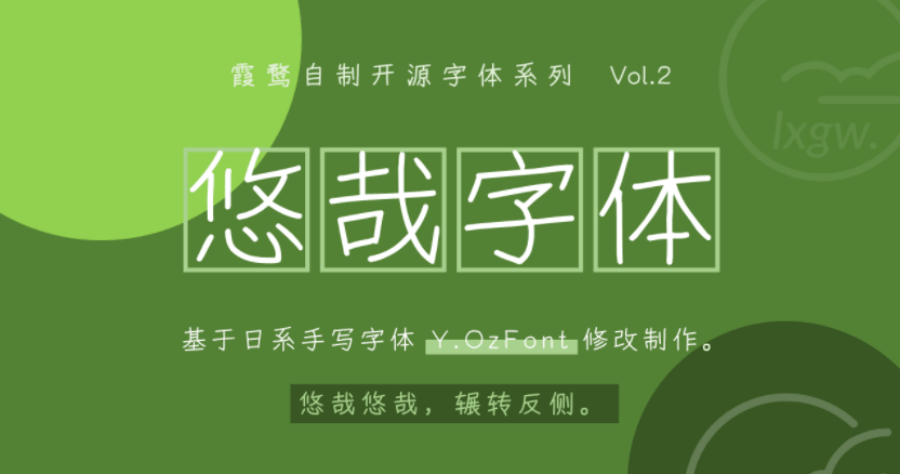
想安裝風格不同的「手寫字體」嗎?最近小編發現「悠哉字體」,完全免費可商業使用,「悠哉字體」是基於日文字體 Y.OzFont 修改、調整造出的新字體,並且補上對應的中文字(繁體字、簡體字都有),共有 4 個字重,使用「悠哉字體」完全無須付費且標明原作者,在找手寫字體的朋友們趕快收下放心使用吧。喜愛手寫字體的你,絕不能錯過小編整理的可商用手寫字型 9 款免費下載,趕快去通通收下吧。
支援的中文字相當齊全,包含了 GB 2312 範圍內的所有漢字,也就是超過 6700 個中文字體。
在原 Y.OzFont 的基礎上,字面縮小至原來的 95%,優化英文和標點符號的顯示;修改部分漢字的寫法,使其接近中文字的寫法。